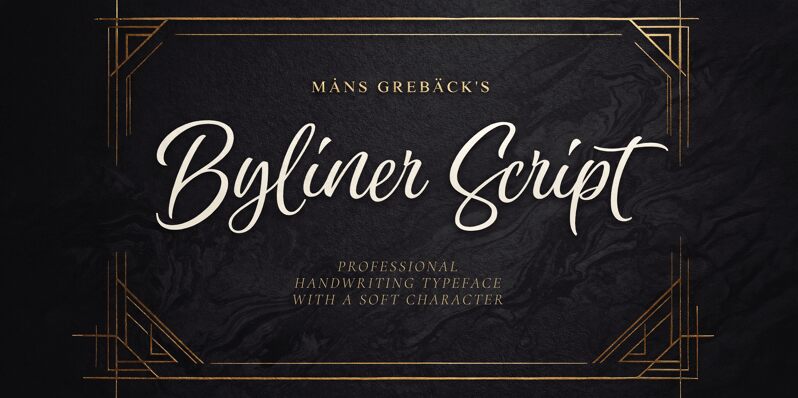
Byliner Script, de Mans Greback AB, es una tipografía caligráfica gratuita que evoca la ligereza de la rotulación clásica. Sus letras presentan trazos largos y en bucle con uniones suaves, combinando un inicio abierto y fluido con curvas más estilizadas para lograr un estilo relajado y elegante, como si hubiera sido escrita con mano firme y rápida.
Es perfecta para proyectos de branding, packaging de tiendas, portadas de revistas, menús de cafeterías o papelería de bodas, donde buscas una fuente gratuita con un toque más personal que una script estándar. Úsala en titulares cortos, logotipos o monogramas cuando quieras que sus generosos bucles y trazos ascendentes sean los protagonistas.